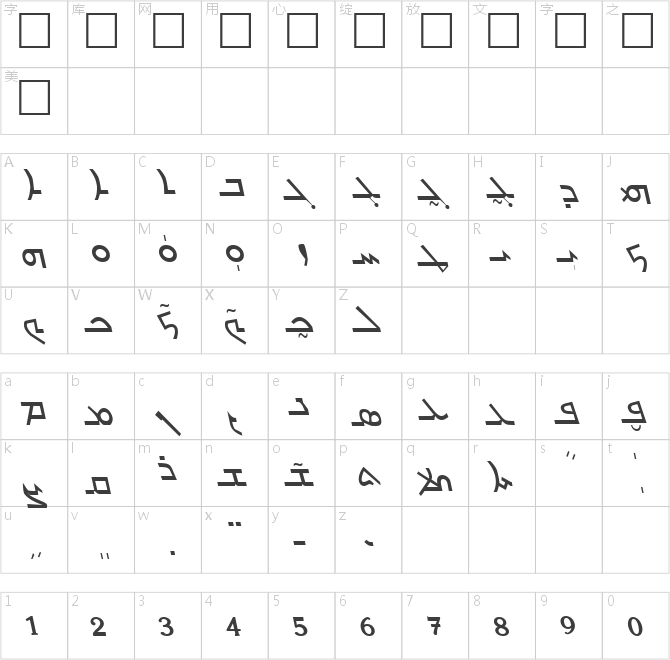
字體名稱: carloi
carloi
carloi介紹
carloi字體字庫是一款讓人賞心悅目、百看不厭的非英字體,適合各類廣告和產(chǎn)品包裝設(shè)計應(yīng)用,字體大小0.05MB,格式為ttf字體,上傳用戶是Me / ,yD ,作者/版權(quán)方為未知
carloi效果圖